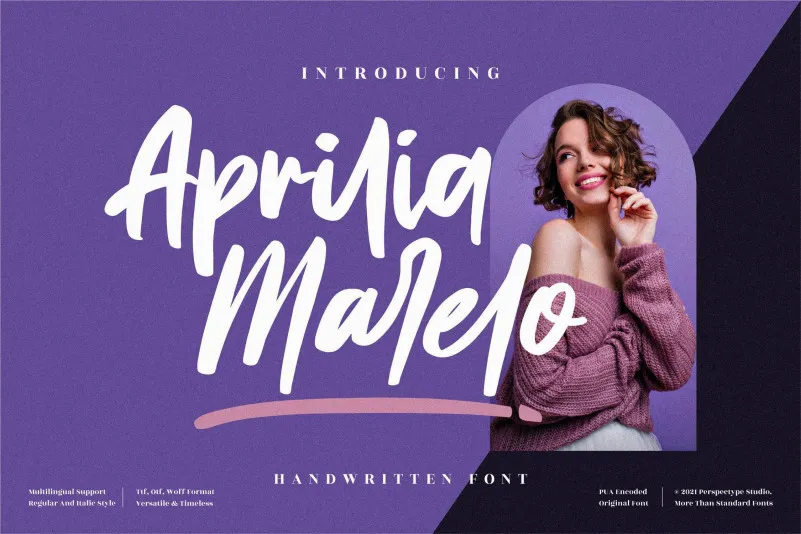
Aprilia Marelo Font – Download Grátis
A fonte “Aprilia Marelo” é uma elegante e agressiva fonte escrita a mão criada para dar personalidade aos seus headlines e logotipos. Suas letras são fortes, confiantes e dinâmicas, tornando-a perfeita para projetos que buscam um toque de estilo. Com o PUA encoding, ela oferece acesso fácil a todos os gílios e swashes, adicionando um charme nostálgico aos seus designs. Perfeito para aqueles que procuram uma fonte visualmente atraente e sofisticada para dar seu design aquela pitada especial de estilo único.